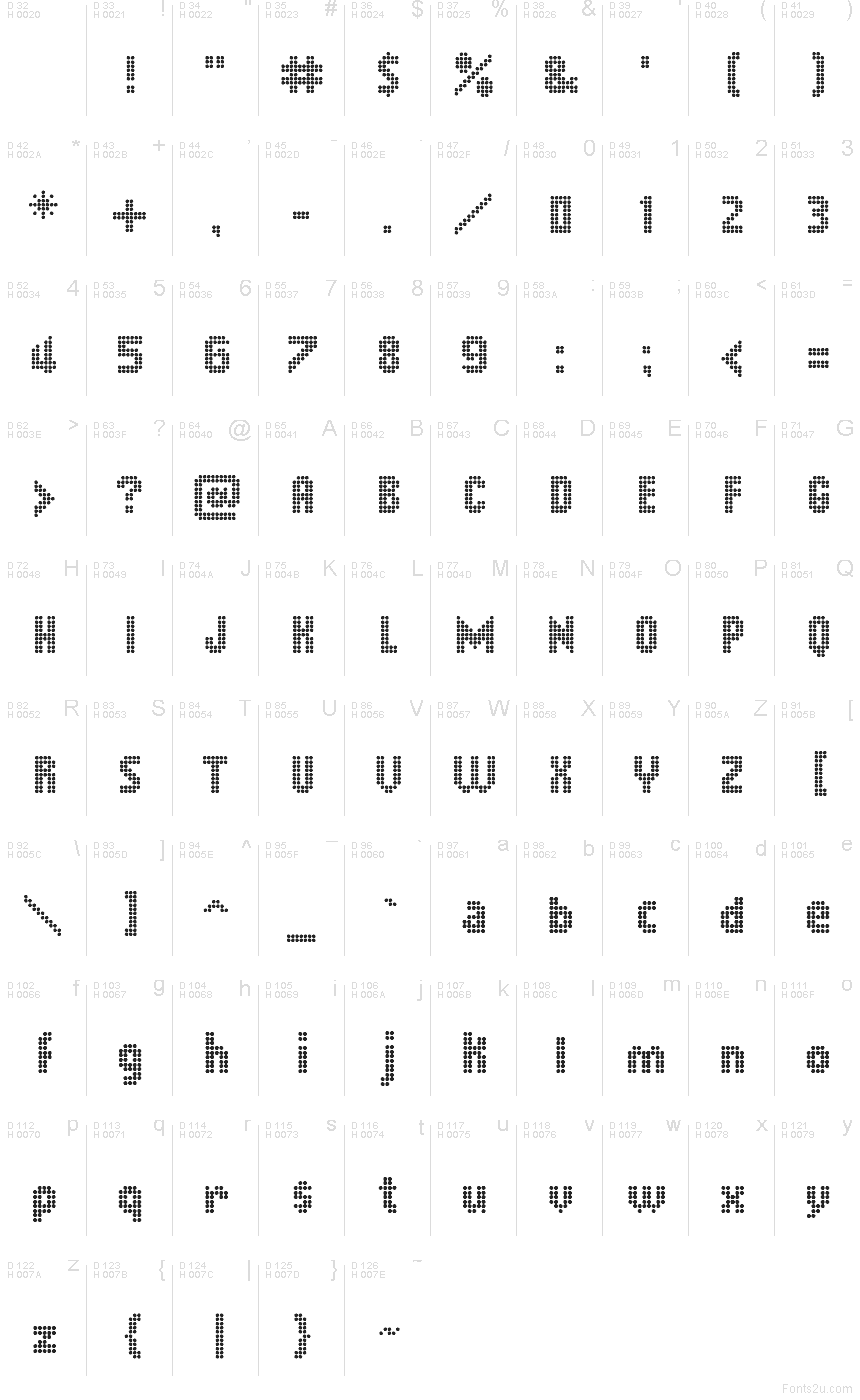
Dot Spot di Galdino Otten è un font display gratuito a matrice di punti con un'anima retro-digitale giocosa. Le lettere sono costruite con punti tondi uniformemente distanziati, dando al font un ritmo morbido e vivace che ricorda più le insegne luminose o le prime grafiche digitali che un sistema geometrico rigido.
Si adatta perfettamente a poster, flyer musicali, eventi per bambini, packaging e titoli per i social media, dove le parole brevi possono valorizzare la texture punteggiata. Essendo un font gratuito, è ideale anche per loghi, testi di copertina e monogrammi, poiché il motivo circolare ripetuto conferisce anche alle parole più semplici una presenza luminosa e strutturata.